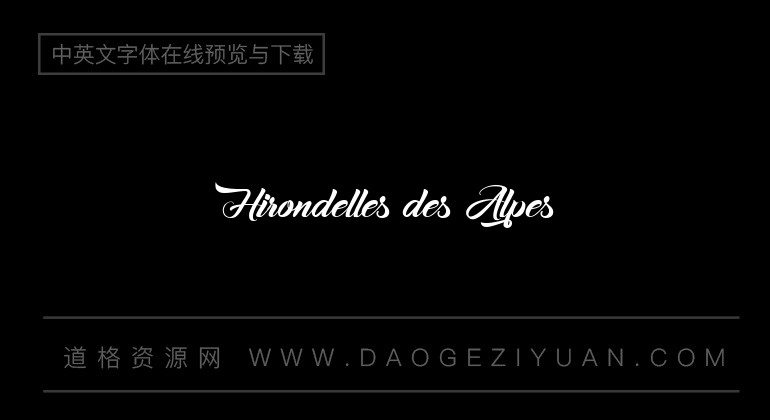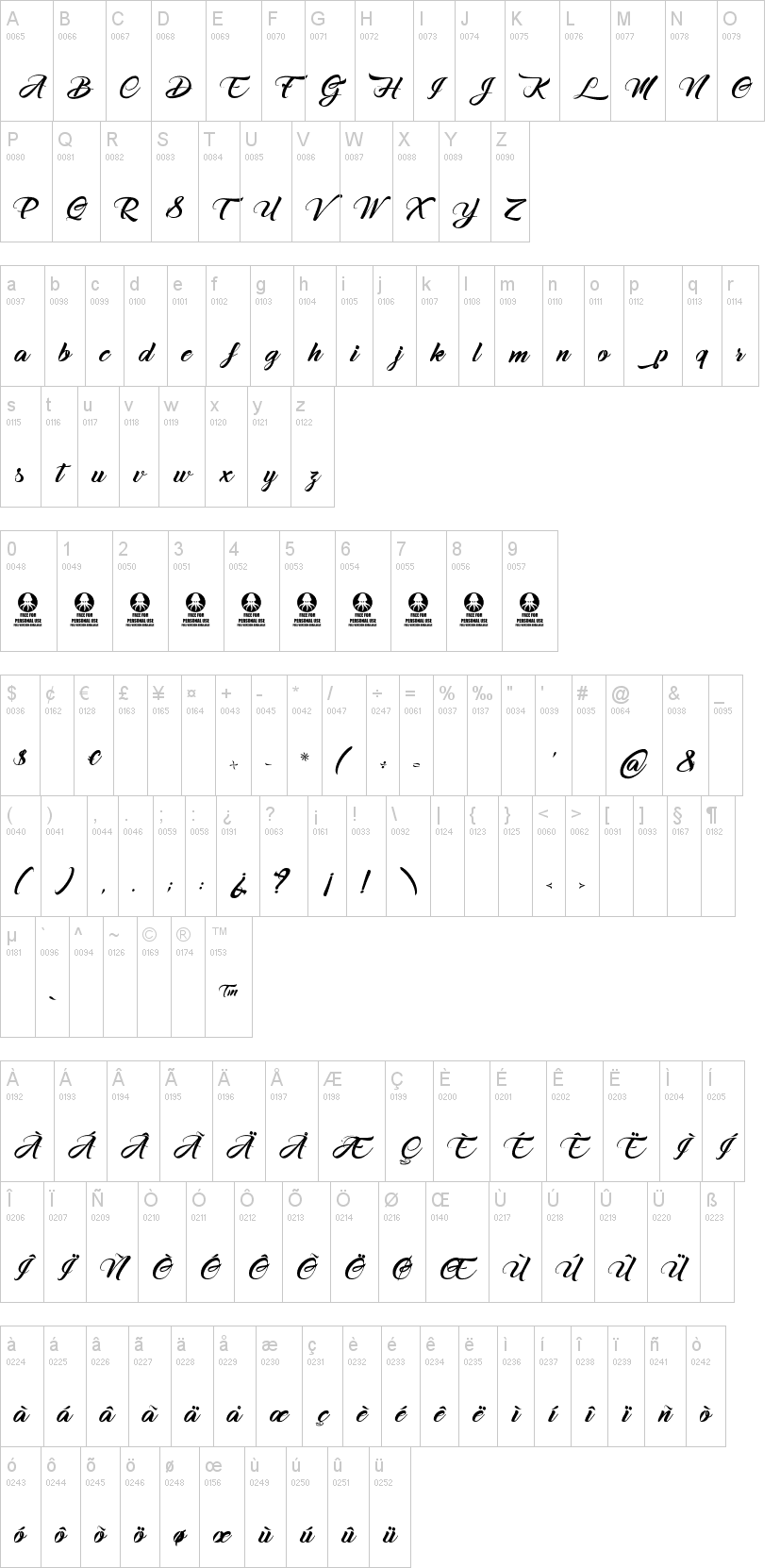
Hirondelles des Alpes
Hirondelles des Alpes 是一种装饰性手写字体,字母的形状仿照燕子的图案设计而成。该字体由设计师 Karolina Lach 创建,灵感来自于她在阿尔卑斯山地区观察到的燕子。 Hirondelles des Alpes 字体的特点是线条细腻,形似手写,字母间距离适中。它适用于一些特殊场合的设计,比如山区旅游宣传、户外装饰等等。在设计中,Hirondelles des Alpes 字体通常与其他简单的字体搭配使用,以突出其装饰性。 Hirondelles des Alpes 字体可免费下载,也可以在许多字体库中找到。
Hirondelles des Alpes是一款非常不错的手写艺术字体,具有很好的视觉感,适合于文化类的宣传设计、商业类品牌的广告和产品包装设计以及个性化文字排版等较多场景。